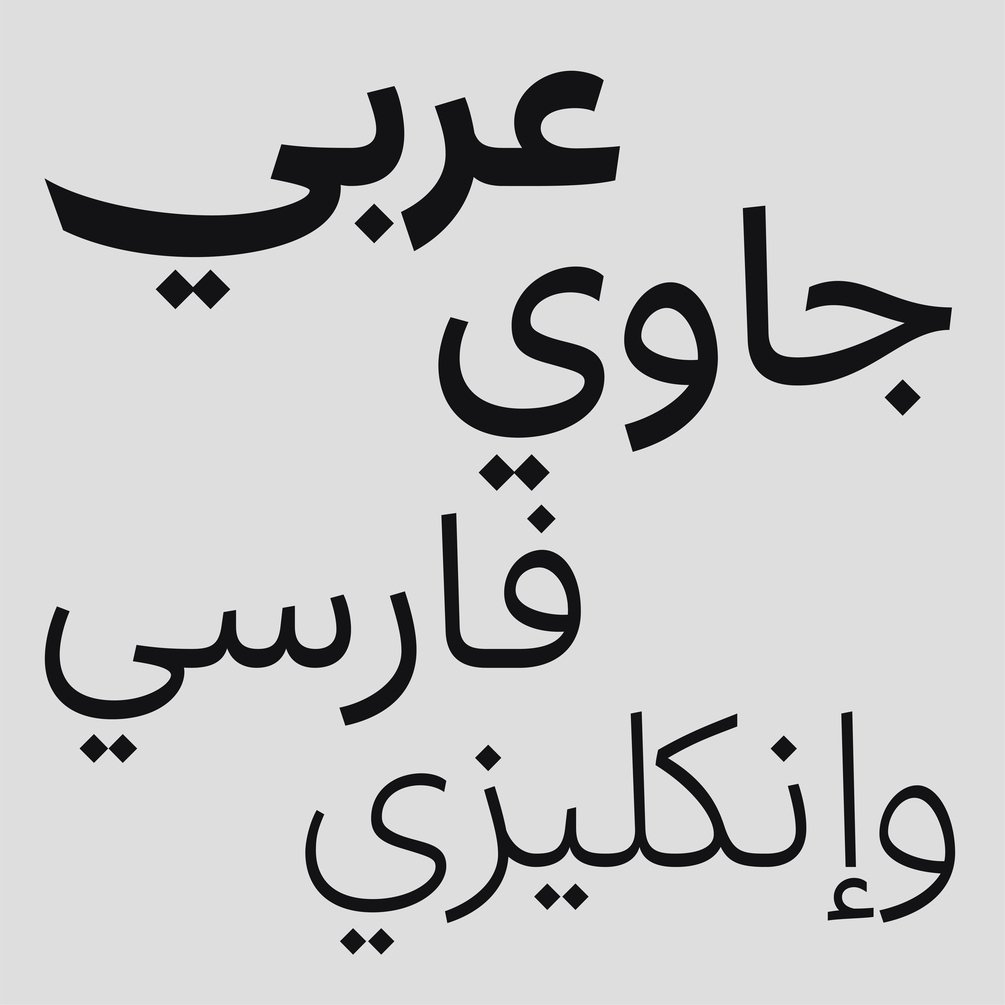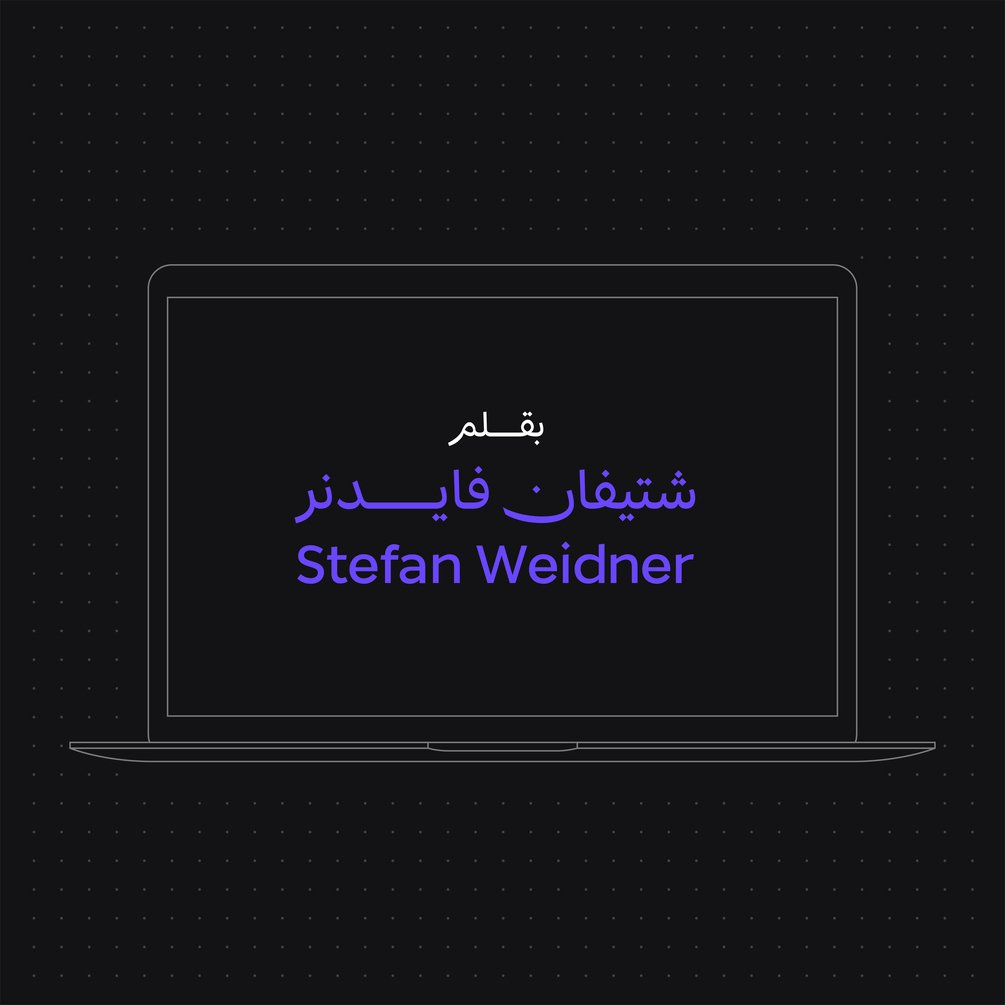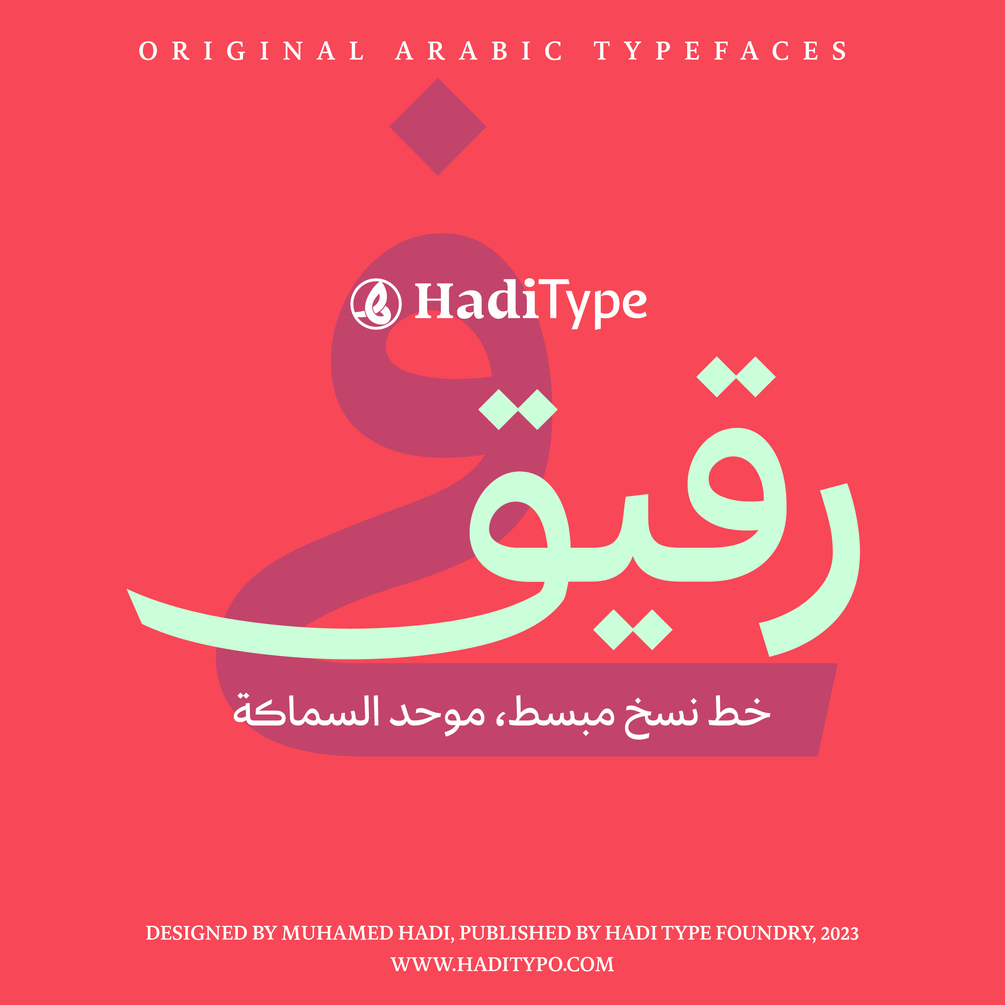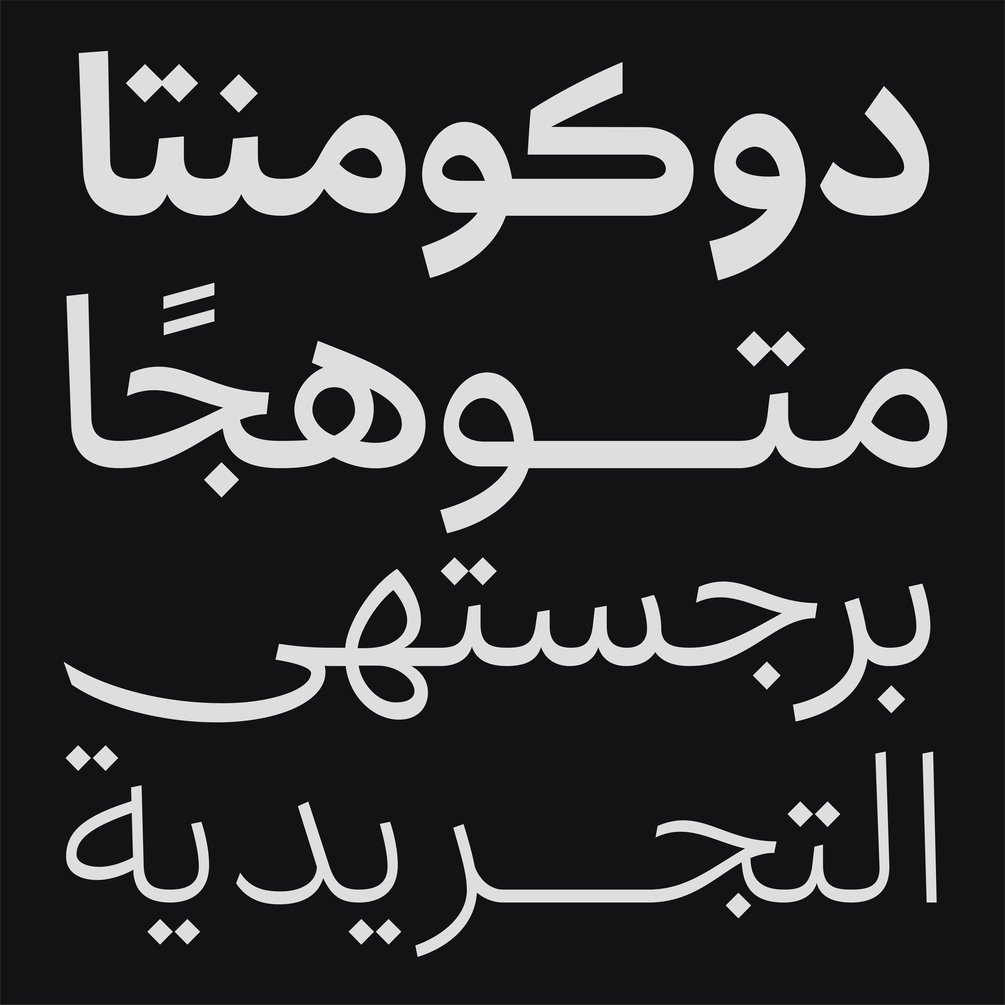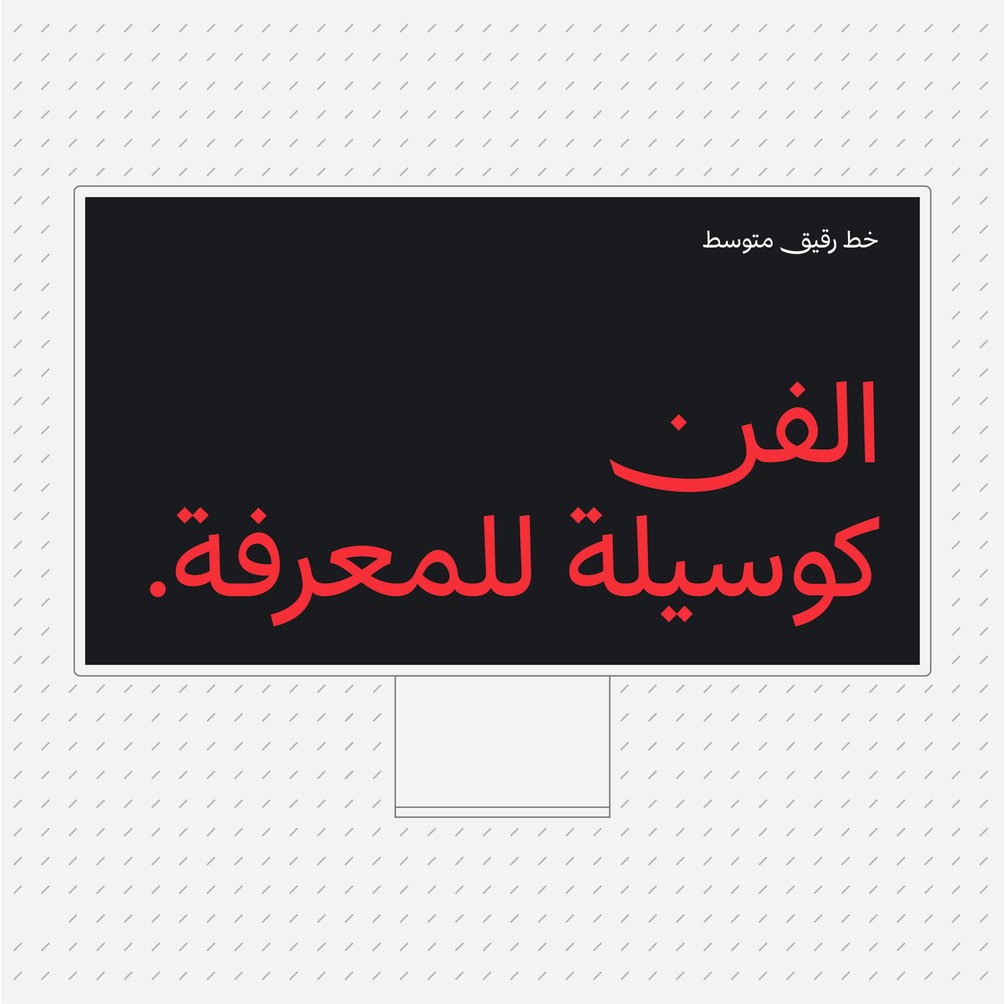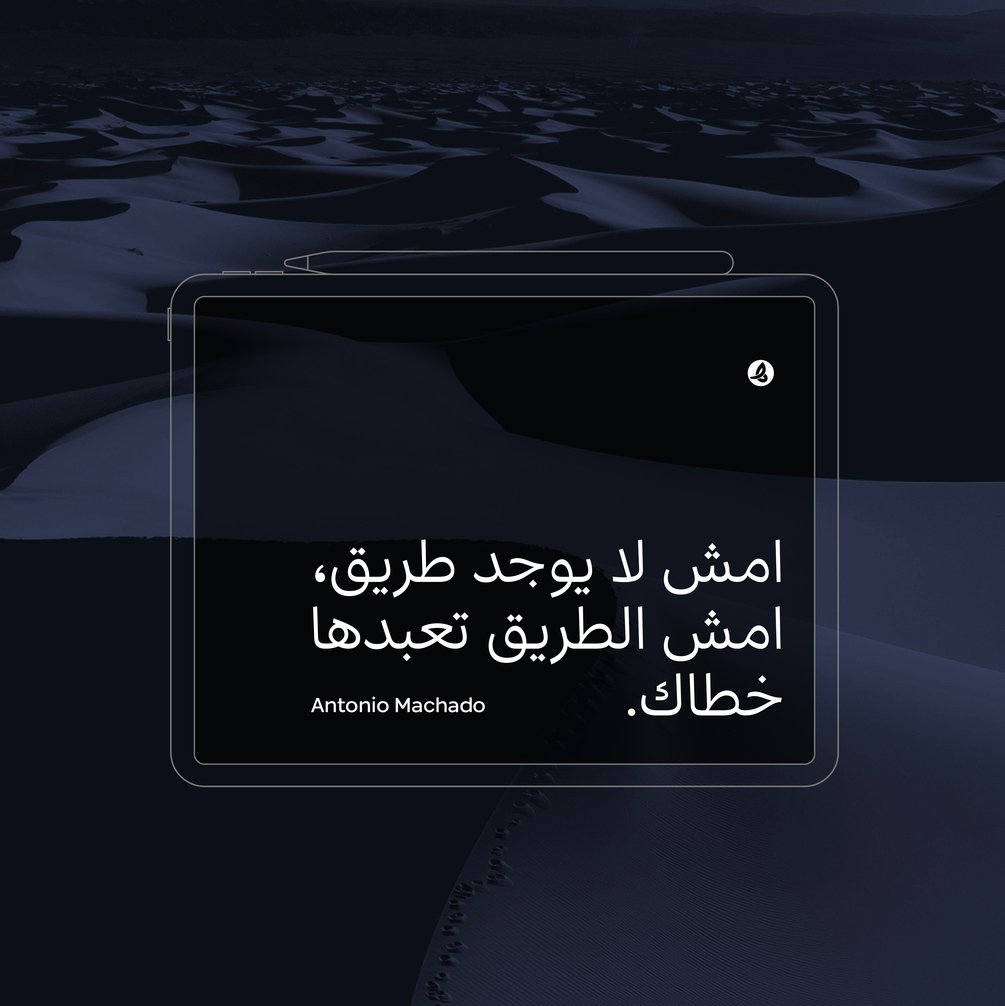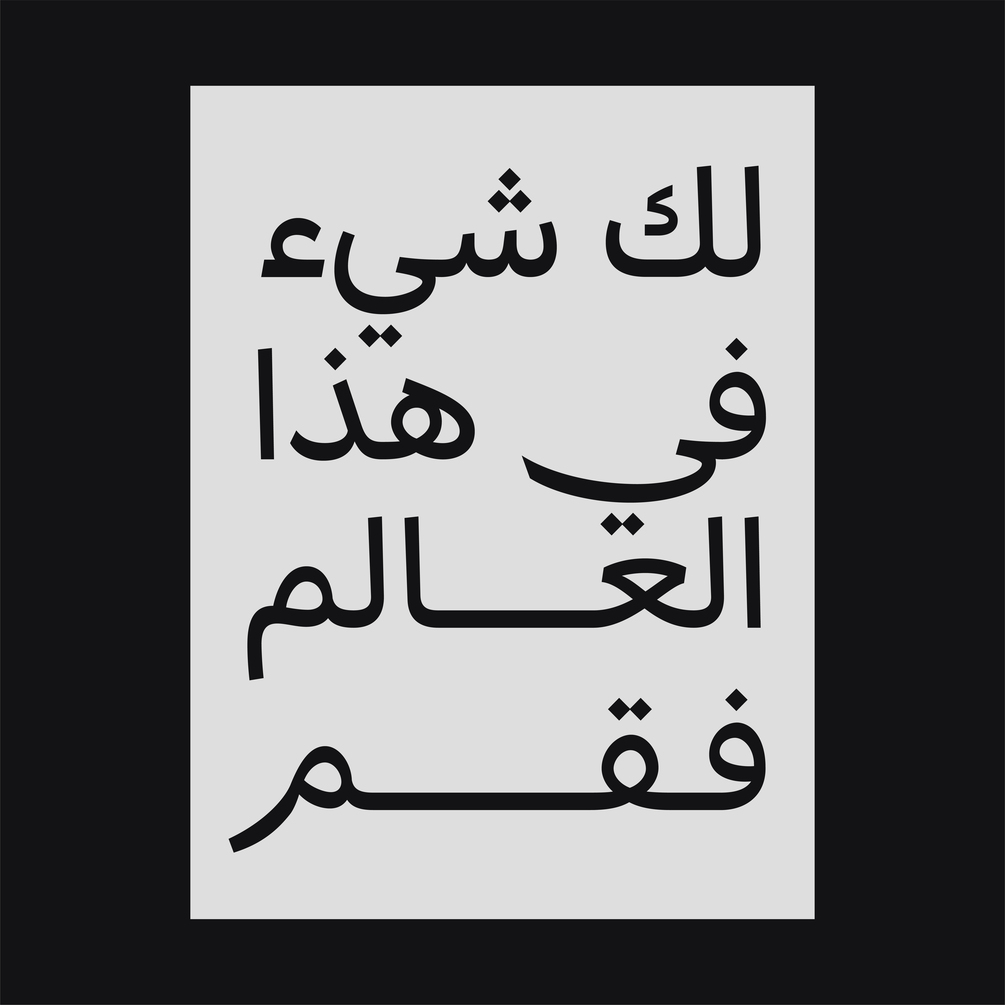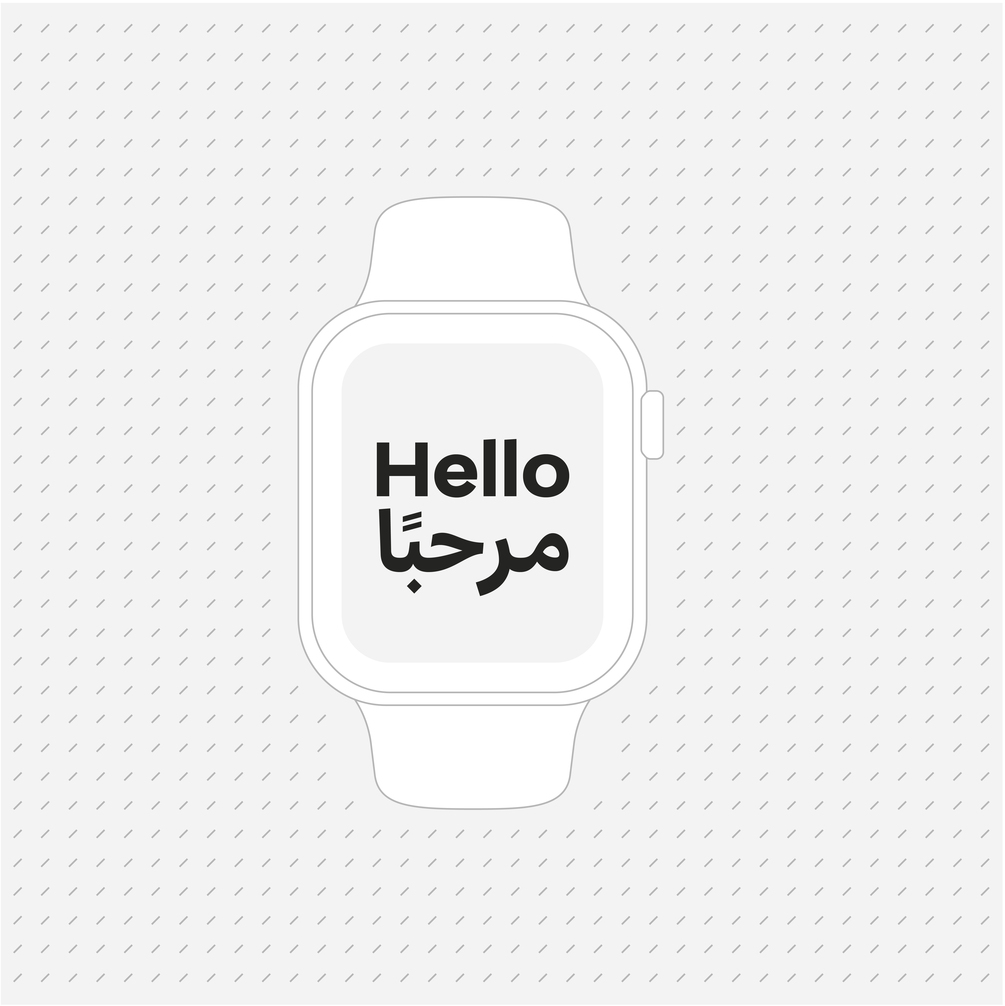
HT Rakik
HadiType Foundry
خط رقيـــــق
خط نسخ مبسَّط، موحد السماكة.
في الآونة الأخيرة تم استحداث نمط جديد من تصميم الحروف العربية استندت الى خط النسخ المبسط، مثل خط Tahoma الذي تم إنشاؤه بواسطة شركة Microsoft لمواجهة تحديات العرض على الشاشة، خاصة في الأحجام الصغيرة في مربعات الحوار والقوائم.
ثم سرعان ما تناولت الفكرة أيدي المصممين على إعادة تطوير هذا النوع من الخط، كنوع من الخروج على صور الحروف المعتادة التي أصبحت تقدمها الخطوط الكوفية المعاصرة.
لمواكبة هذا التطور البصري والتقني يسعدني أن أقدم لكم خط «رقيــق»، وهو من طراز خط النسخ المبسَّط والموحد السماكة، مع لمسة عربية في معالجة حروفه لتعطي نكهة عربية تضيف الى الكتابة بالخط العربي في العصر الرقمي.
الخط يحتوي على عدة لغات؛ اللغة العربية والجاوي والأردية والفارسية واللغة اللاتينية الأساسية، كما يحتوى على خمسة أوزان متفاوتة السمكات لتعطي المصمم الحرية في توظيف الخط في مشاريعه المختلفة.